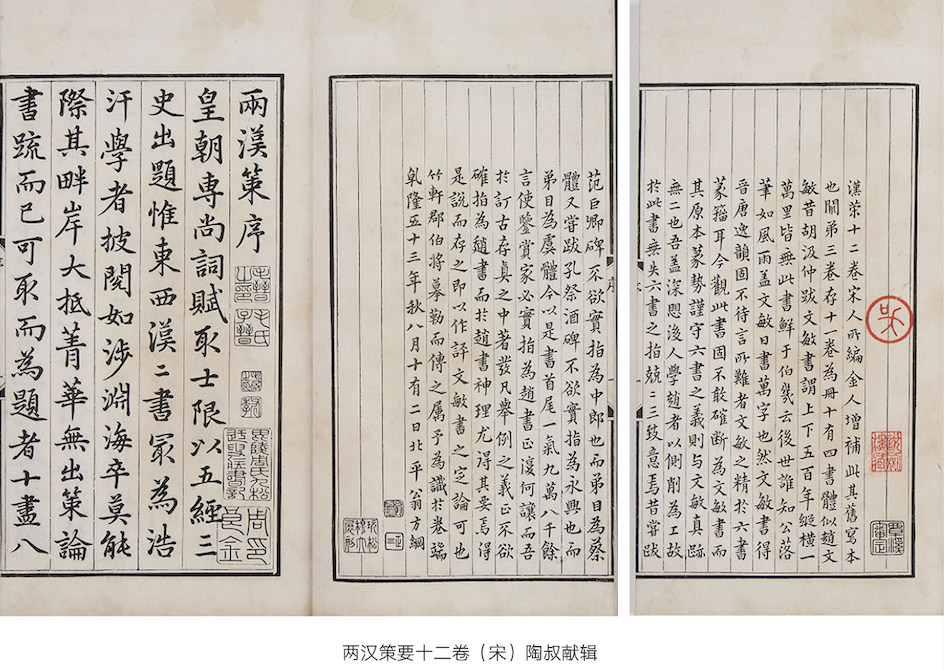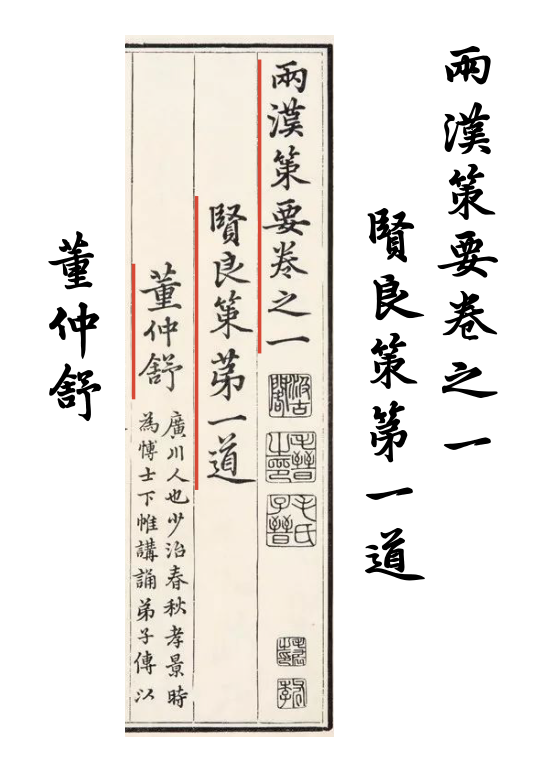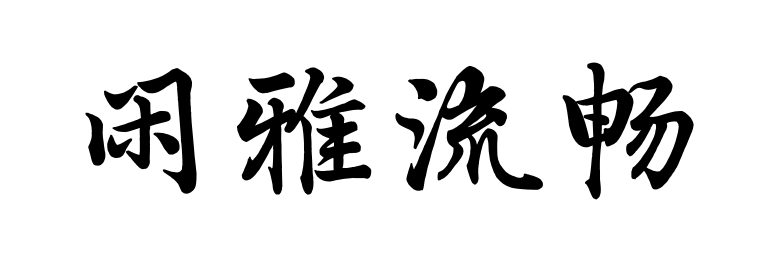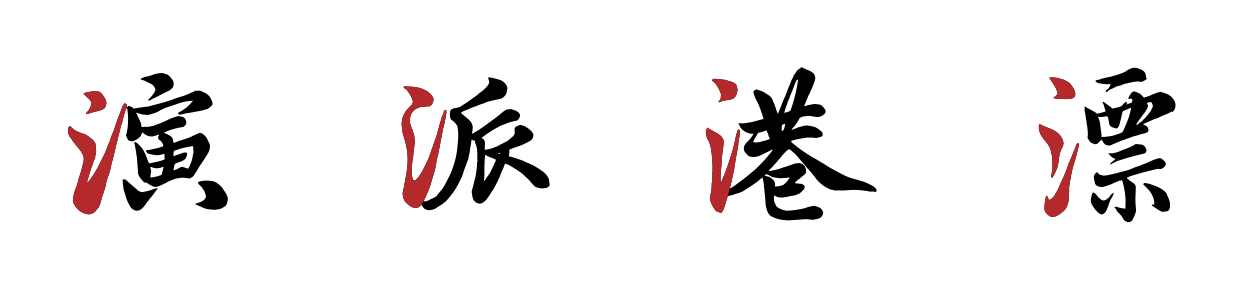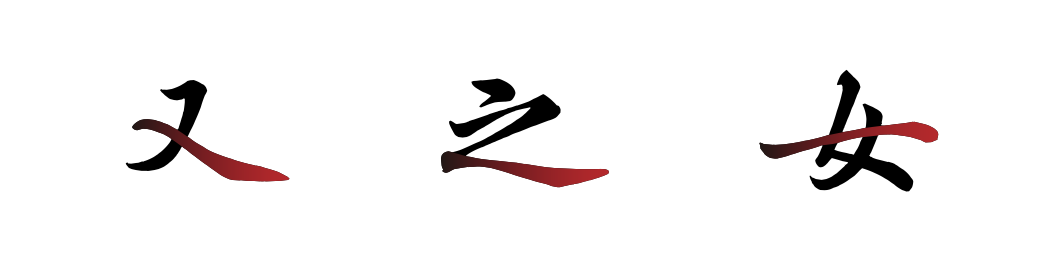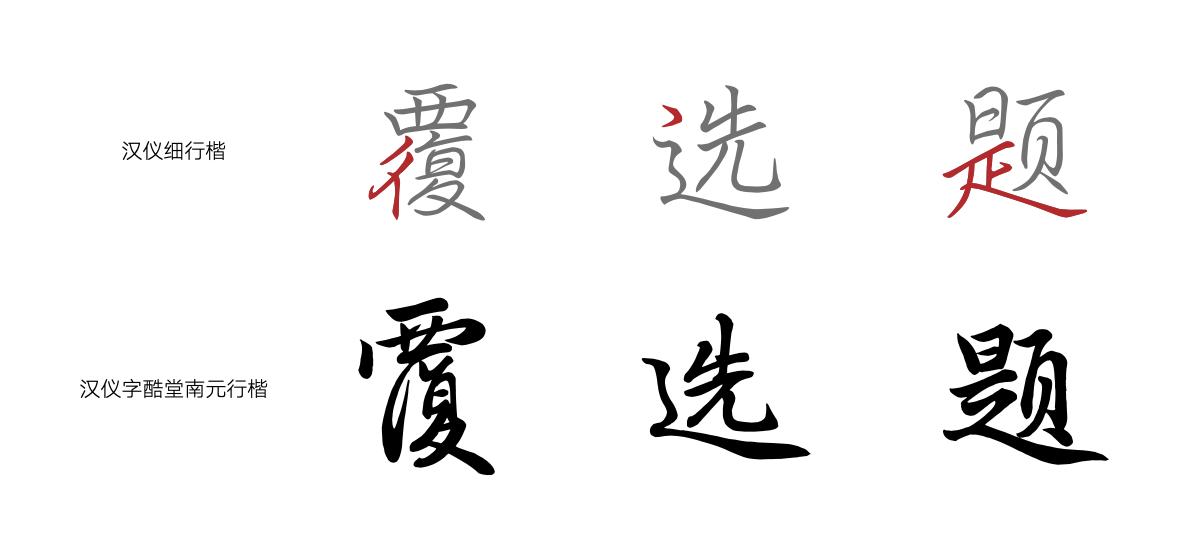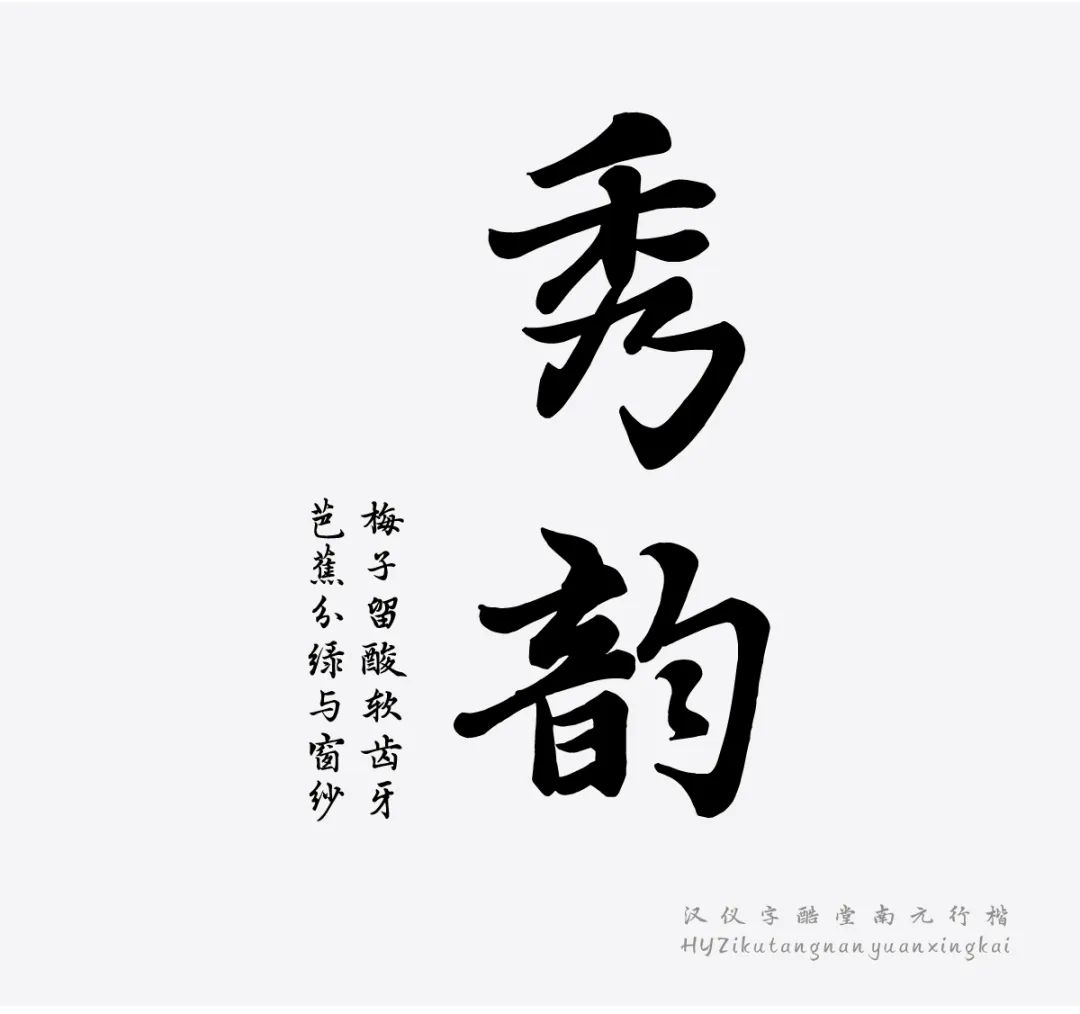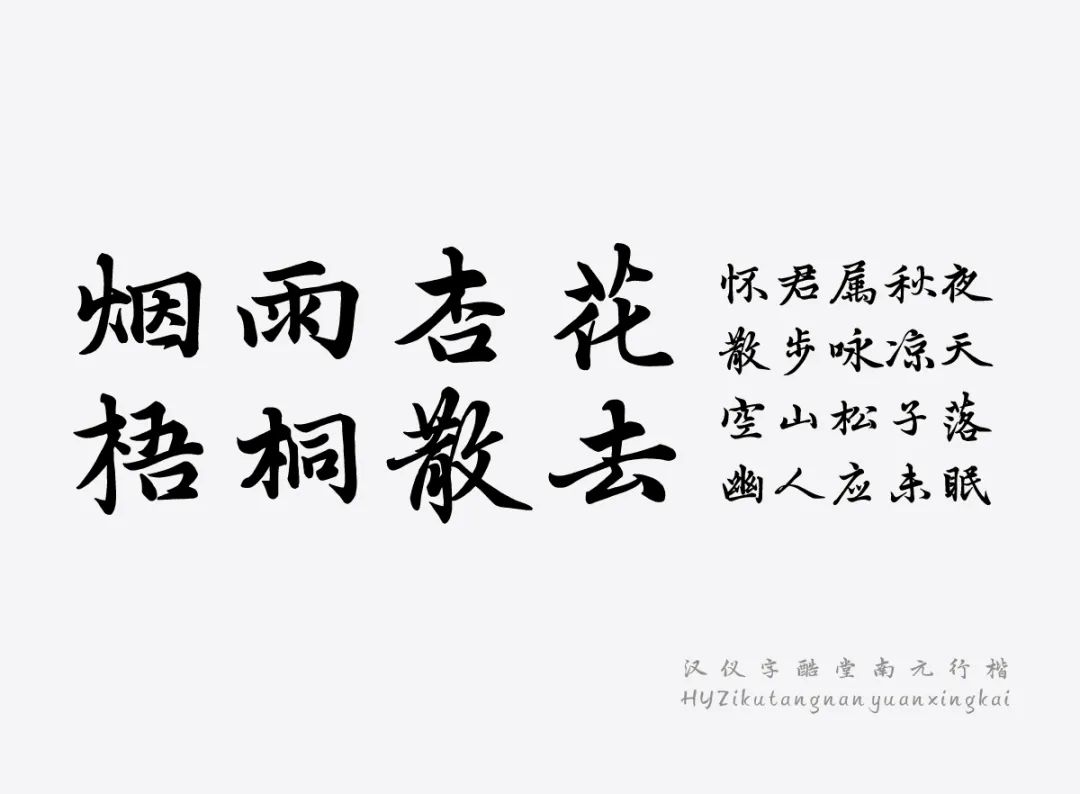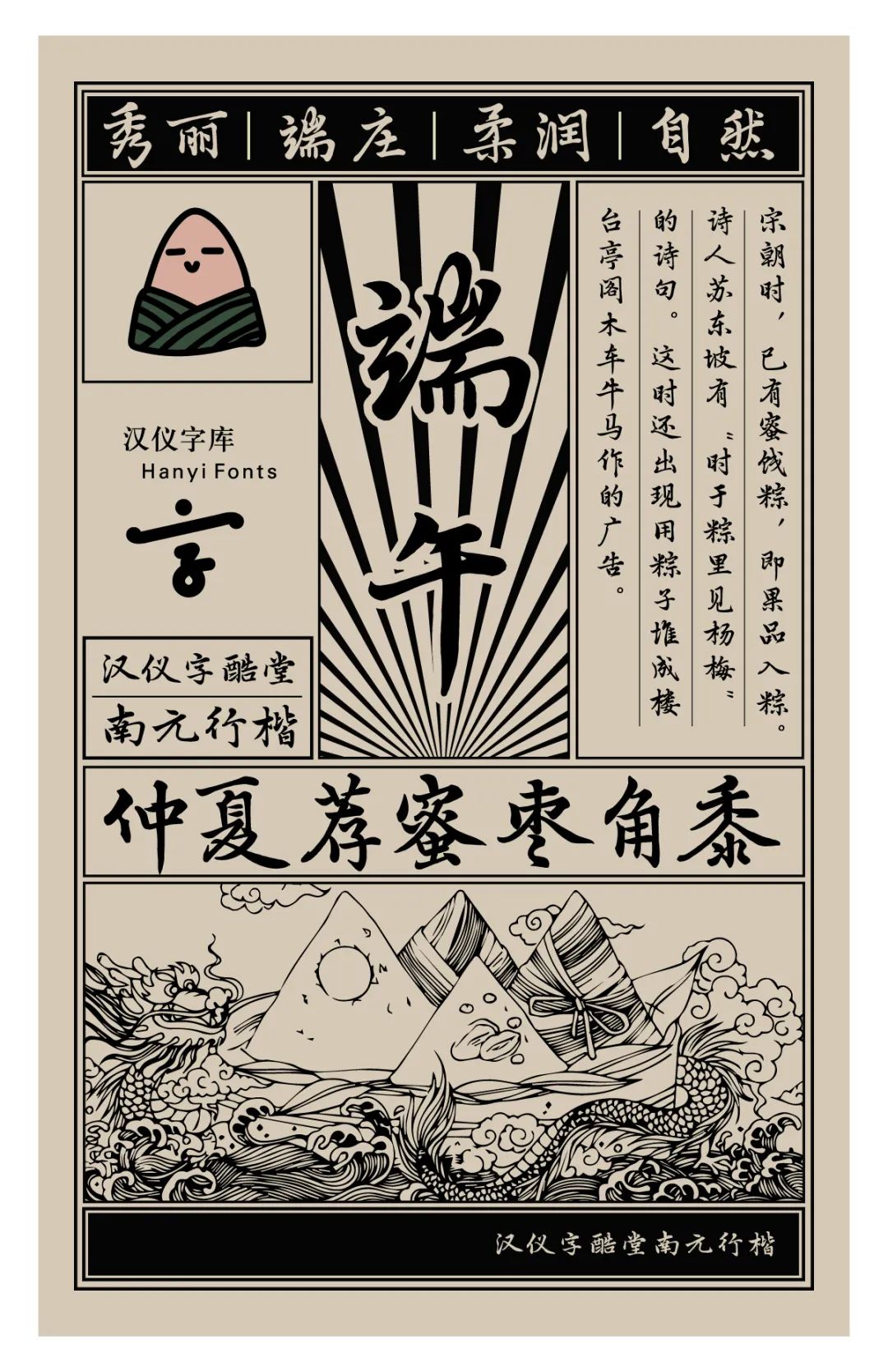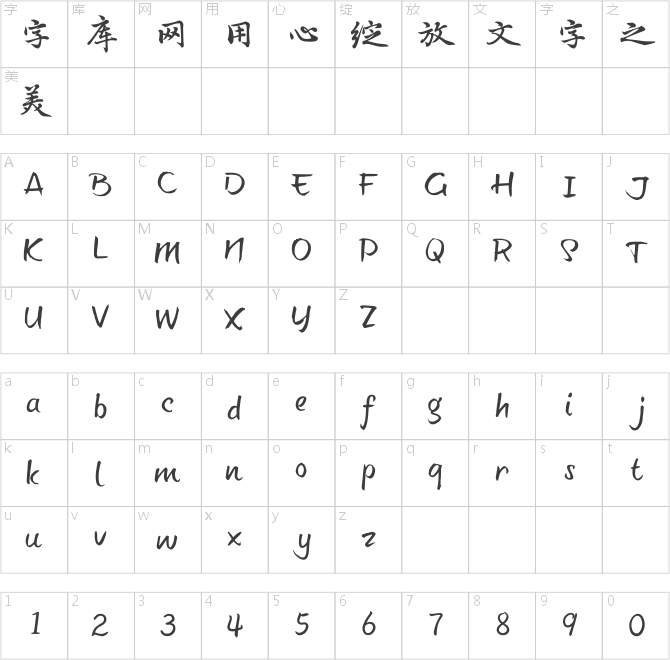
漢儀字酷堂南元行楷 詳情頁
字體名稱: 漢儀字酷堂南元
漢儀字酷堂南元行楷
字體來源
漢儀字酷堂南元行楷源自《兩漢策要》?!秲蓾h策要》由宋朝陶叔獻(xiàn)編輯,收錄了兩漢期間164篇重要的政論文章,歷代盛傳為元代書法大家趙孟頫手書。序文后有翁方綱審定評(píng)題,稱:“不欲確指為趙書,而于趙書神理,尤得其要焉?!爆F(xiàn)存版本為清乾隆56年(1791)贛郡守張竹軒鉤摹影刊元寫本。
字體風(fēng)格
漢儀字酷堂南元行楷作為一款復(fù)刻字體,字體工整秀麗,筆法穩(wěn)健。既保留了唐楷的法度,又不拘泥于唐楷的一招一式,在字體中保留一些生動(dòng)俊俏的行書筆法與結(jié)構(gòu),筆劃形態(tài)生動(dòng)自然,可從中看到趙孟頫書法的一些風(fēng)格特征。
字體特點(diǎn)
漢儀字酷堂南元行楷的字形間架方正,結(jié)體嚴(yán)謹(jǐn)端莊,重心平穩(wěn),布白均勻,點(diǎn)畫之間彼引呼應(yīng)十分緊密。外似柔潤而內(nèi)實(shí)堅(jiān)強(qiáng),形體端秀而骨架勁挺。
漢儀字酷堂南元行楷的結(jié)字自由,字的筆畫根據(jù)不同連筆位置作出靈活多樣性的改變。點(diǎn)畫之間多前后呼應(yīng),筆意相連。有的甚至干脆就用行書的寫法,筆畫與筆畫之間有牽絲映帶。
漢儀字酷堂南元行楷的撇畫、捺畫以及橫畫比較舒展,字勢橫展。筆畫騰挪起伏,有曲折之美。
漢儀字酷堂南元行楷為書寫簡便,將一些字的偏旁部首做了省減和變形,使字體更加流美遒勁、生動(dòng)活潑。